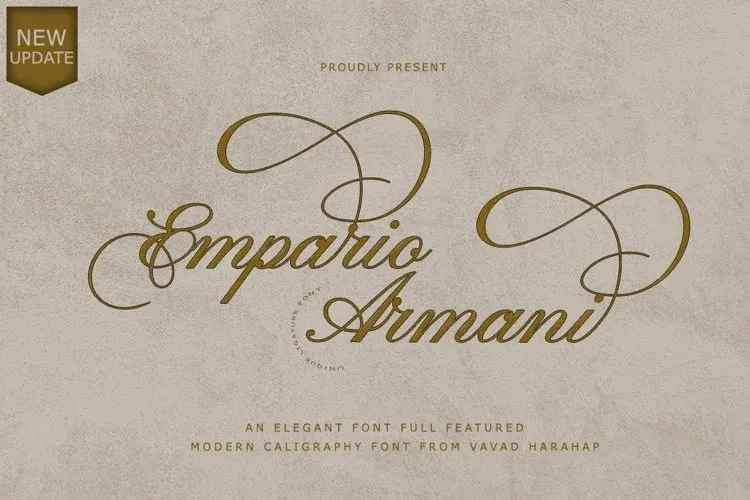
A Empario Armani Font é uma nova opção moderna para designers que buscam uma script elegante e feminina. Criada pelo designer vavadharahap na plataforma 99designs, essa fonte incorpora elementos chamativos e delicados ao seu design. Ela oferece uma variedade de aplicações, desde o uso em logotipos de produtos até gráficos vintage, cards de casamento e roupas de marcas. Seu estilo arrojado é perfeito para agregar um toque sofisticado aos seus projetos. Com a Empario Armani Font, você pode explorar infinitamente as possibilidades criativas que essa nova opção proporciona para o design.